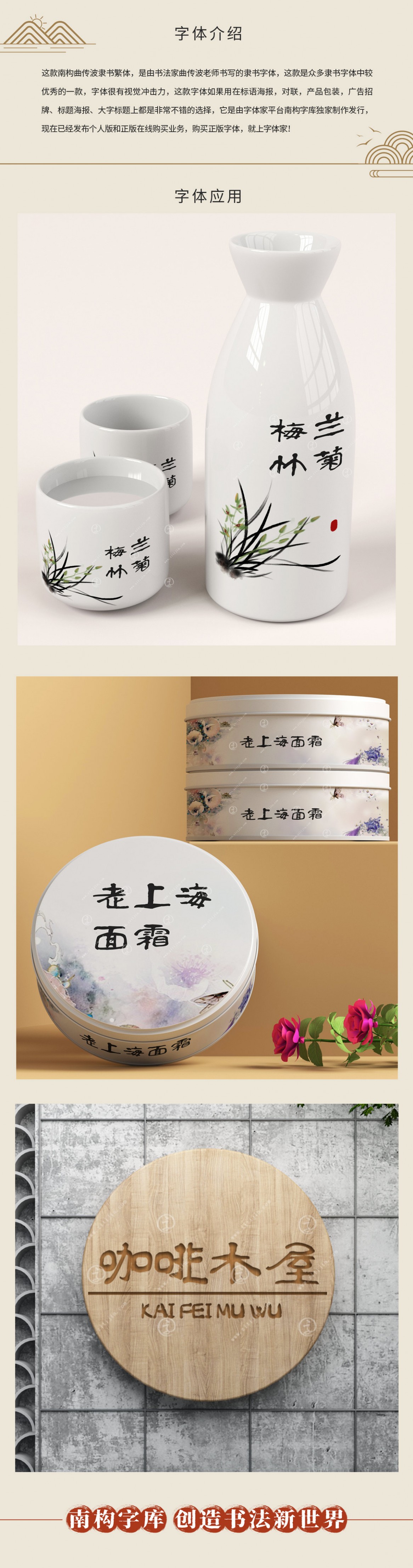
南構(gòu)曲傳波隸書(shū)
是由書(shū)法家曲傳波老師書(shū)寫(xiě)的隸書(shū)字體,曲傳波老師不僅發(fā)布了隸書(shū)字體,還發(fā)布了草書(shū)和隸書(shū)繁體,這款隸書(shū)還有一款同樣風(fēng)格的繁體隸書(shū),隸書(shū)字體相對(duì)于其他字體來(lái)說(shuō),適用范圍會(huì)更廣,這款是眾多隸書(shū)字體中較優(yōu)秀的一款,特別推薦給朋友們,這款字體如果用在標(biāo)語(yǔ)海報(bào),產(chǎn)品包裝,廣告招牌上都是非常不錯(cuò)的選擇,由字體家平臺(tái)南構(gòu)字庫(kù)獨(dú)家制作發(fā)行,現(xiàn)在已經(jīng)發(fā)布個(gè)人版和正版在線購(gòu)買業(yè)務(wù),購(gòu)買正版字體,就上字體家!